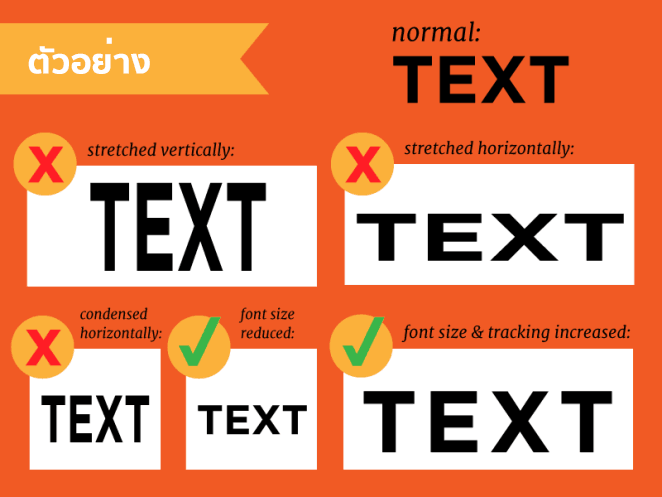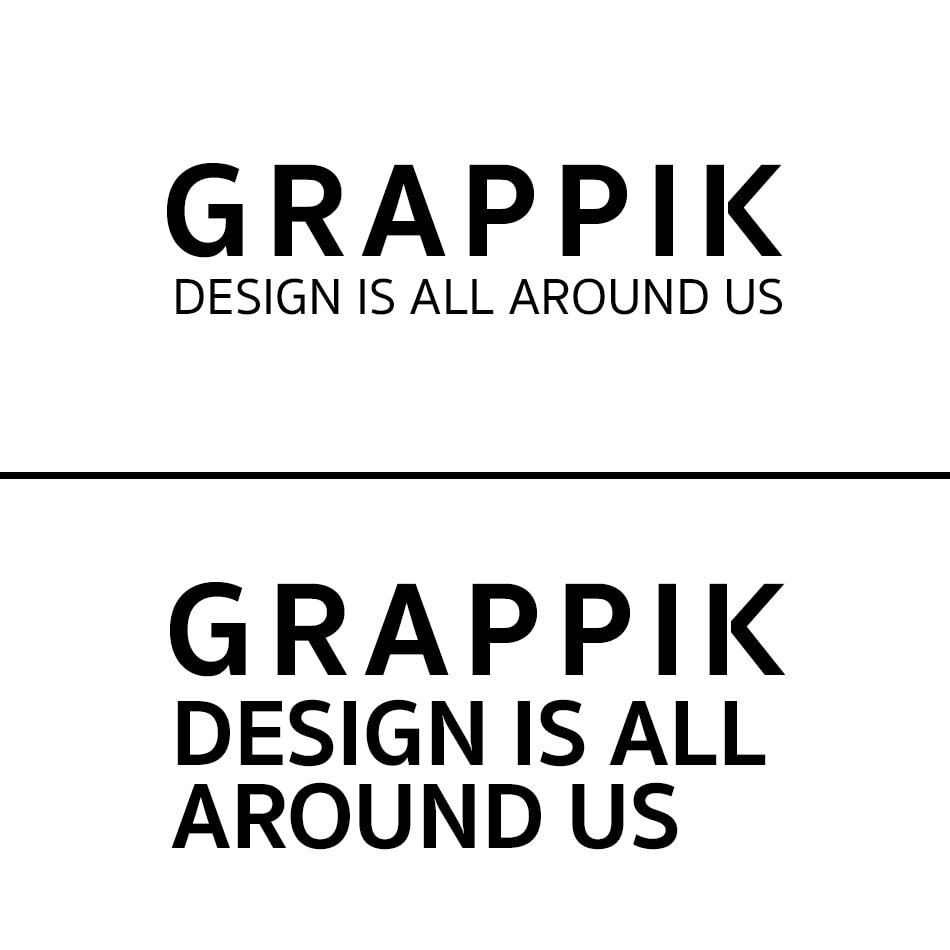
การออกแบบที่ดีนั้นไม่ใช่เพียงแค่การเลือกสีและการจัดองค์ประกอบภาพเท่านั้น การวางตัวอักษรให้สวยงามและอ่านง่ายเป็นอีกปัจจัยที่จะทำให้งานออกแบบของคุณออกมาสวยงาม ดังนั้นถ้าคุณต้องการที่จะได้ออกแบบงานของคุณให้สวยเพอร์เฟคคุณต้องเรียนรู้กฏการจัดวางตัวอักษร 20 ข้อนี้
1. ให้พื้นที่ตัวอักษร
การให้พื้นที่กับตัวอักษรจะทำให้คนอ่านไม่รู้สึกปวดตาหรืออึดอัดเกินไป ลองคิดเล่นๆดูว่าคุณกำลังมองวิวเมืองแล้วเห็นถนนมีแต่รถเต็มไปหมดคุณจะรู้สึกอึดอัดรึเปล่า ? ตัวอักษรก็เช่นเดียวกันให้พื้นกับตัวอักษรแล้วงานออกแบบของคุณจะดูไม่อึดอัดจนเกินไป
2. เว้นบรรทัดให้พอเหมาะ
การเว้นบรรทัดให้พอเหมาะพอดีเป็นอีกหนึ่งจุดที่หลายๆคนลืมให้ความสำคัญ การเว้นระยะห่างระหว่างบรรทัดมีผลต่อการอ่านมาก เพราะถ้าคุณเว้นระยะบรรทัดมากเกินไปคนอ่านจะต้องกวาดสายตาให้มากขึ้นและแน่นอนครับ อาการปวดตาจะตามมาทีหลังอย่างเลี่ยงไม่ได้
3. อย่าย่อ “สเกล” จนเพี้ยน
อีกหนึ่งผิดพลาดที่ไม่สามารถให้อภัยได้ คือการที่คุณย่อหรือเพิ่มขนาดตัวอักษรแต่คุณย่อแบบไม่ดูสเกลของตัวอักษรเลย บางคนย่อจนตัวอักษรบิดเบี้ยวจนหมดรูป อย่าเชียวนะครับ เวลาย่อทุกครั้งอย่าลืมกด Shift ไปด้วยทุกครั้งเพื่อให้เกิดความเคยชิน หรือถ้าคุณไม่อยากจะกด Shift ให้คุณเพิ่มเป็นตัวเลขขนาดแทนจะดีกว่าการย่อขยายเองมากๆเลยครับ
4. ทำสีสันให้ดึงดูด
ถ้าอยากให้คนสนใจในงานของคุณ คุณจะต้องออกแบบและจัดวางตัวอักษรของคุณให้สามารถอ่านได้ง่าย และหลักการง่ายๆที่จะมาช่วยให้งานของคุณมีพลังดึงดูดมากขึ้นก็คือการเลือกสีสันให้คนอ่านสามาถอ่านได้ง่าย เลือกสีให้ตัดกัน จะสามารถทำให้อ่านได้ง่ายมากขึ้น
5. เลือก Font ให้ดี
Font บาง Font ไม่เหมาะกับการอ่านที่เยอะๆหรอกนะ Font แต่ละตัวจะมีคุณสมบัติเฉพาะตัว เพราะงั้นคุณจะต้องเลือกดีๆเพื่อที่งานของคุณจะได้ไม่เละเทะ
6. จัดการติ่งข้อความ
หลายคนเจอเนื้อหายาวๆที่ต้องนำมาออกแบบและจัดวาง พยายามเว้นบรรทัดจัดหน้าให้ดูดีที่สุดแต่ในการจัดทุกครั้งมันจะมี “ติ่ง” ข้อความหลุดออกมาเสมอ เพราะงั้นอย่าทิ้งมันไว้ให้โดดเดียวพามันกลับเข้าไปในประโยคด้วย เพื่อที่จะได้ประหยัดเนื้อที่และประโยคจะได้ไม่ขาดหาย
7. อย่าใช้ Font หลายตระกูล
นักออกแบบหลายคนชอบติส 1 ประโยคจัด Font 7 ตระกูล บ้าไปแล้ววววววว !! มันรกเกินไป 1 ประโยคควรจะมี Font ไม่เกิน 3 ตระกูล เพื่อที่จะทำให้ประโยคนั้นไม่รกจนเกินไป
8. เลือก Font ให้เข้ากับงาน
การเลือก Font ให้เหมาะสมกับงานเป็นเรื่องที่เราต้องใส่ใจให้มากที่สุด หลายคนออกแบบงานมาอย่างดีแต่พอเลือก Font แล้ว บอกได้คำเดียว เลือก Font ผิดชีวิตเปลี่ยน
9. อย่าใช้ Effect ตัวอักษรสุดเห่ย
Effect ของ Font ที่มากับโปรแกรมต่างๆ ขอร้องเลยครับว่า อย่า (หรือถ้าเลี่ยงไม่ได้ก็ใช้ให้น้อยที่สุด) ลองเปลี่ยนมาเน้นความหนาให้ Font หรือ ใช้สีให้เด่นๆแทนดีกว่า เพราะ Effect ที่มีให้พวกนั่น มันช่างล้าสมัยและโบราณซะเหลือเกิน
10. ใหญ่บ้างเล็กบ้าง
ถ้าจะพาดหัวอะไรสักอย่างนึงคุณลองนึกดูนะว่ามันจะมีคำที่ต้อง เน้น และ ไม่เน้น ถ้ามันขนาดเท่ากันหมดหรือหนาเท่ากันหมด มันจะดึงความสนใจไปหมด ลองปรับให้ใหญ่บ้างเล็กบ้างดู